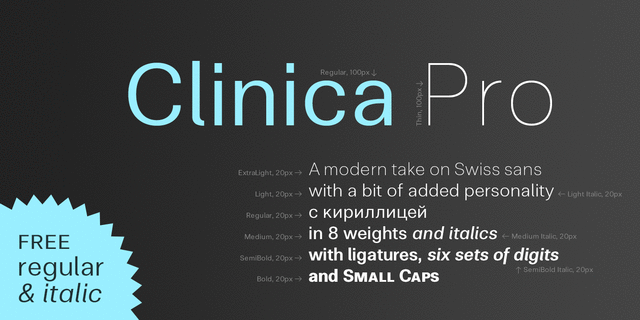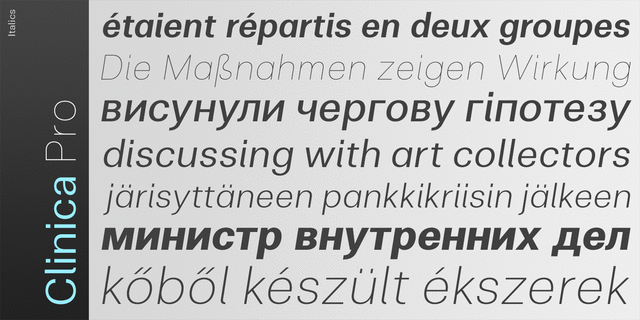
Clinica Pro – современный, достаточно нейтральный швейцарский гротеск с индивидуальными чертами в 8 весах с курсивом. Содержит 6 наборов цифр, капитель и множество лигатур. Шрифт разработал и выпустил Андрей Константинов в студии Mint Type в 2013 году.
деликатный, чистый, легкий, прохладный, свежий, модный, городской, деловой, серьезный, стабильный, статичный, устойчивый, офисный, строгий, глобализированный, глобалистичный, простой, ровный